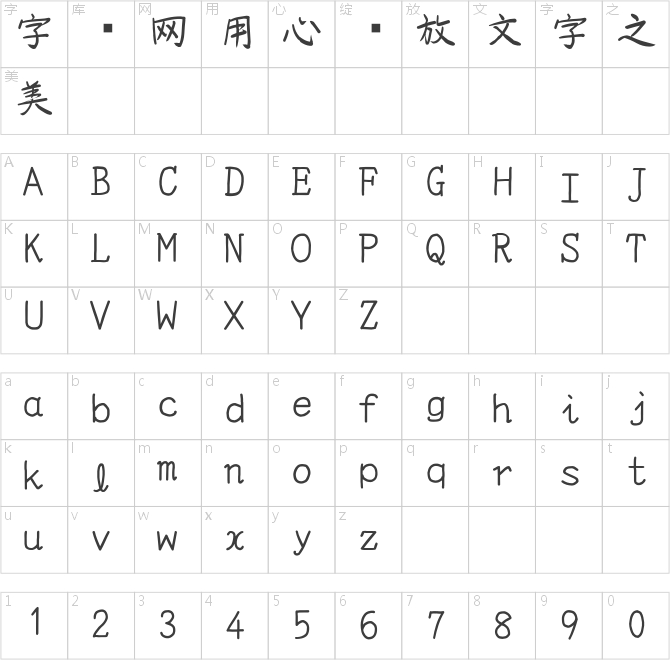
YOzFont鋼筆字體是手寫風(fēng)格的字形。這個字體筆畫干凈利落,筆觸上帶著手寫的筆鋒,看上去挺不錯的。只可惜這是日本設(shè)計(jì)的制作的字體,對簡體中文支持較差,對繁體支持很好。
YOzFont鋼筆字體YOzFontK鋼筆字體字庫是一款讓人賞心悅目、百看不厭的日文字體,適合各類廣告和產(chǎn)品包裝設(shè)計(jì)應(yīng)用,字體大小7.35MB,格式為TTC字體,上傳用戶是Pt.趙鵬濤,作者/版權(quán)方為Y.Oz